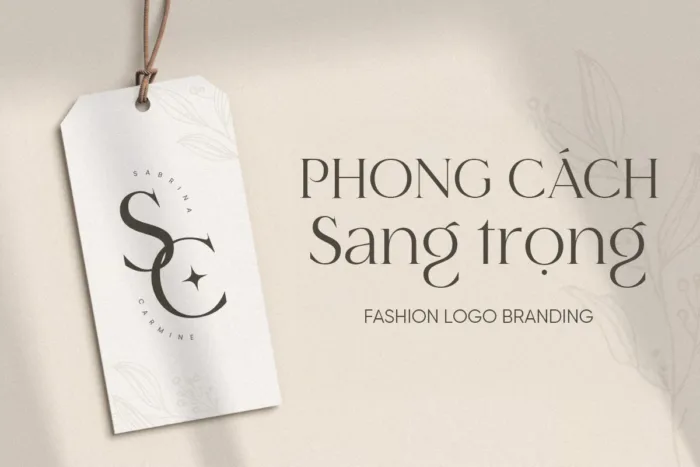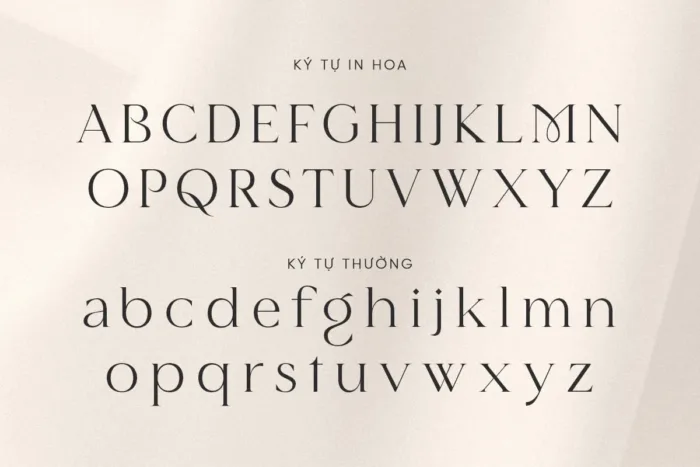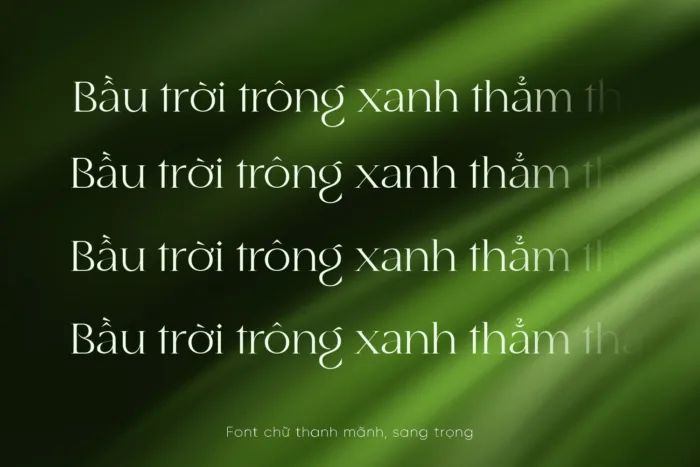
DVN Maelis Việt hóa – Font Serif chữ mỏng và tinh tế
DVN Maelis Việt hóa là một kiểu chữ mang phong cách thanh lịch, hiện đại và đầy chất thơ. Với các đường nét mảnh mai, độ tương phản nhẹ giữa các nét đậm – nhạt, font chữ này tạo cảm giác nhẹ nhàng như một làn gió thoảng. Từng chữ cái được thiết kế tỉ mỉ, mang lại vẻ duyên dáng và tinh tế, lý tưởng cho các thiết kế cao cấp, thời trang, mỹ phẩm hoặc ấn phẩm nghệ thuật.
Bản Việt hóa được chăm chút kỹ lưỡng để giữ nguyên tinh thần của bản gốc, đồng thời tối ưu hóa khả năng sử dụng trong ngữ cảnh tiếng Việt – với đầy đủ dấu và ký tự đặc trưng. DVN Maelis là lựa chọn hoàn hảo cho những ai tìm kiếm một font chữ vừa mềm mại, vừa chuyên nghiệp, mang hơi hướng nữ tính nhưng không quá ủy mị. Một sự cân bằng tuyệt vời giữa cá tính sáng tạo và sự tối giản tinh tế.